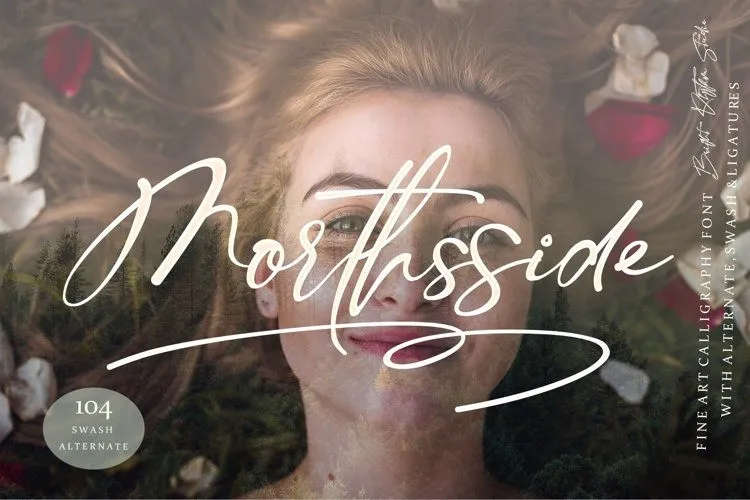
Morthsside Font – Download Grátis
A Morthsside Font é uma elegante escolha para aqueles que buscam um toque delicado e natural no design gráfico. Inspirada na escrita a mão, essa fonte mantém perfeitamente sua característica imperfeita, oferecendo ao designer a oportunidade de criar identidades visuais com um ar atraente e sofisticado. A Morthsside vem em formato TTF, contando com letras maiúsculas e minúsculas, além de alternativas de swash caprichadas. Ideal para criações como logotipos elegantes, embalagens de luxo, cartões de casamento, postais, citações, textos curtos, marcações, design web, gráficos e qualquer outro projeto que busque uma escrita a mão e um toque de beleza. Compostas por um designer chamado Bright Rhythm Studio, essa font é perfeita para quem busca algo mais refinado e natural no seu trabalho visual.